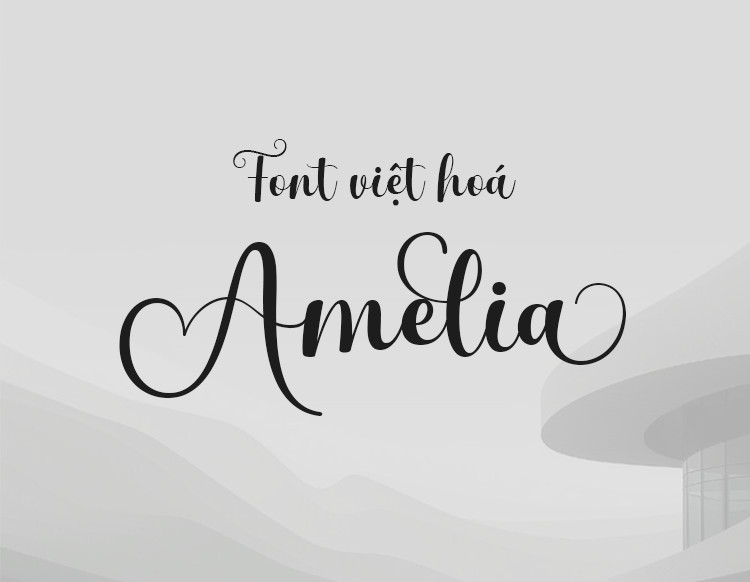
Giới thiệu về Font việt hóa MJ Amelia
Trong thế giới đồ họa hiện đại, việc lựa chọn Font Chữ phù hợp đóng vai trò quyết định đến tính thẩm mỹ của sản phẩm. Font việt hóa MJ Amelia là một bộ phông chữ mang phong cách Script viết tay mềm mại, thanh lịch và đầy cá tính. Với các đường nét uốn lượn tự nhiên, bộ font này giúp các thiết kế trở nên gần gũi nhưng không kém phần sang trọng. Đặc biệt, phiên bản này đã được tối ưu hóa đầy đủ dấu tiếng Việt, giúp các bạn học sinh và giáo viên dễ dàng sử dụng trong học tập cũng như trình bày văn bản sáng tạo.
Đặc điểm nổi bật của Font việt hóa MJ Amelia
Thiết kế mềm mại và linh hoạt
Font việt hóa MJ Amelia sở hữu cấu trúc đường nét mảnh mai, tạo cảm giác bay bổng cho người xem. Đây là lựa chọn hoàn hảo cho các dự án thiết kế thiệp mời, bìa sách hoặc các bài thuyết trình trên lớp. Sự linh hoạt của font cho phép nó kết hợp tốt với nhiều loại phông chữ không chân khác để tạo sự cân bằng.
Ứng dụng thực tế trong giáo dục
Đối với môi trường học đường, bộ font này hỗ trợ đắc lực trong việc làm báo tường, thiết kế tiêu đề bài học hoặc trang trí các bảng tin nội bộ. Nhờ tính năng việt hóa chuẩn xác, người dùng không còn lo lắng về lỗi hiển thị dấu khi gõ tiếng Việt, đảm bảo tính chuyên nghiệp tối đa cho mọi văn bản.
Hướng dẫn sử dụng và kết luận